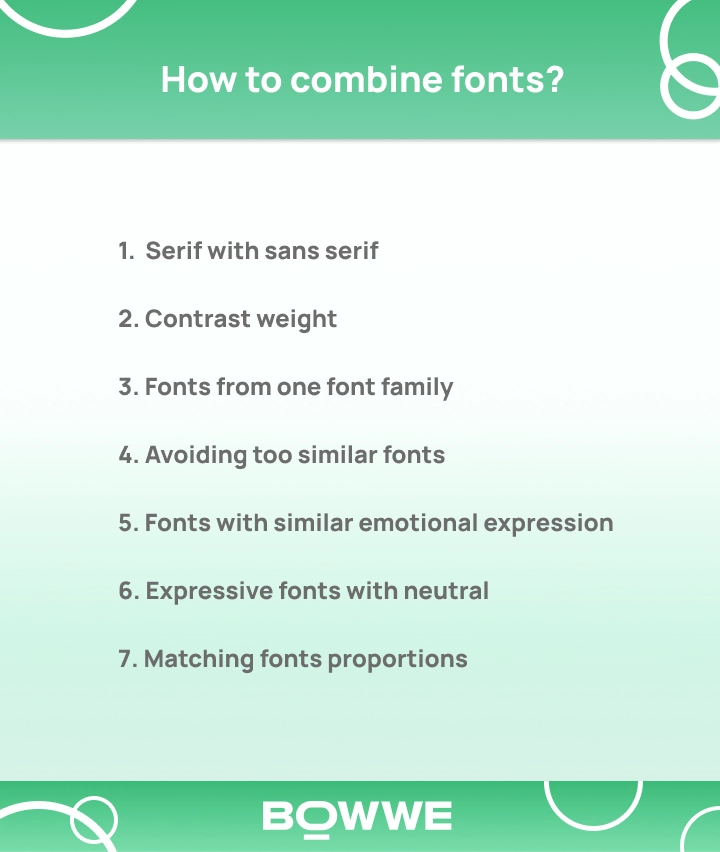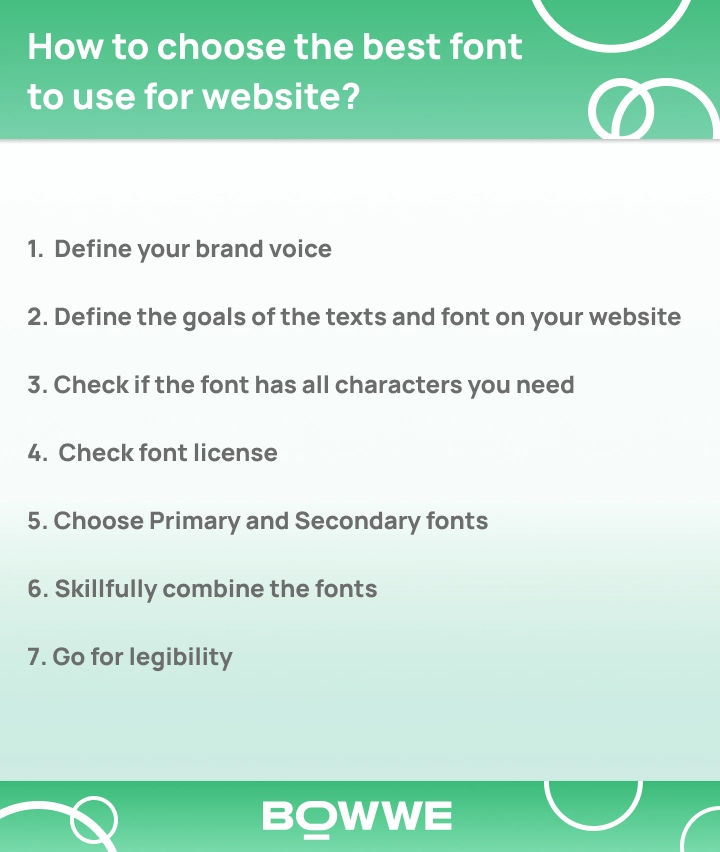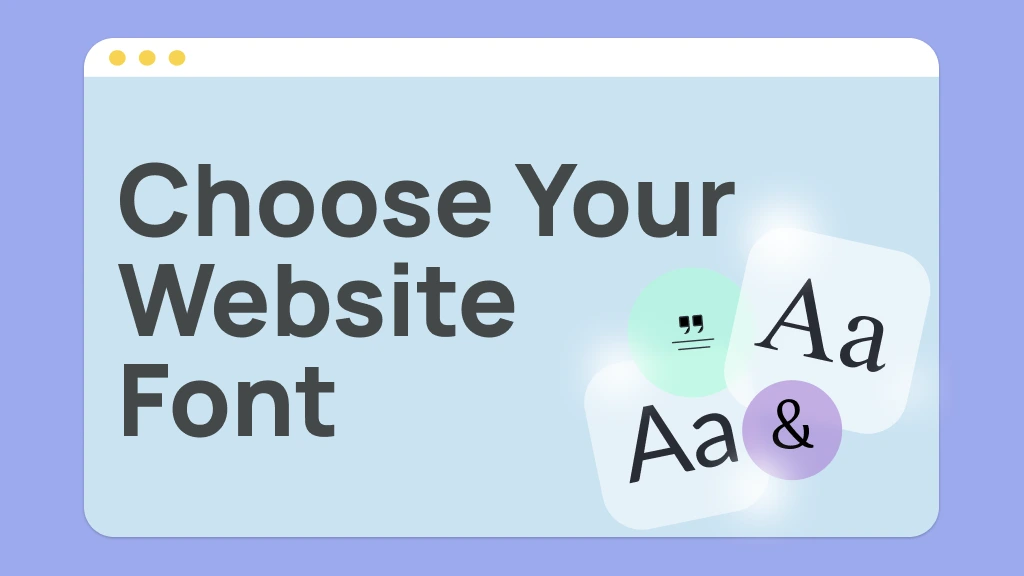
Aktualisieren oder erstellen Sie eine Website von Grund auf neu ? Jetzt ist es an der Zeit, die beste Schriftart auszuwählen. Dies ist eine entscheidende Wahl. Wieso den? Das Layout und Erscheinungsbild von Texten beeinflusst maßgeblich die Ästhetik, Funktionalität und Lesbarkeit der Website. Eine Website mit guten Schriftarten ist viel benutzerfreundlicher und führt zu einer höheren Conversion!
Die Auswahl der besten Schriftart für eine Website ist nicht einfach. Alles, was Sie tun müssen, ist dieser Anleitung zu folgen, um sicherzustellen, dass Sie die beste Webschriftart auswählen!
Wie wählt man die beste Schriftart für die Website aus?
Hier sind die 7 wichtigsten Schritte, die Sie unternehmen sollten!
1. Definieren Sie Ihre Markenstimme
2. Definieren Sie die Ziele der Texte und Schriftarten auf Ihrer Website
3. Überprüfen Sie, ob die Schriftart alle benötigten Zeichen enthält
4. Schriftartlizenz prüfen
5. Wählen Sie primäre und sekundäre Schriftarten
6. Kombinieren Sie die Schriftarten geschickt
7. Achten Sie auf Lesbarkeit
Werfen wir einen Blick darauf, wie man sie in der Praxis herstellt.
Schritt I: Definieren Sie Ihre Markenstimme
Wenn es um Schriftarten geht, ist Ihre Marke alles. Es ist das, was Kunden sehen und womit sie sich identifizieren, wenn sie an Ihr Unternehmen denken. Aus diesem Grund ist es so wichtig, dass Sie die richtige Schriftart für Ihr Unternehmen auswählen. Aber wie bestimmen Sie die Stimme Ihrer Marke? Und wie wählt man eine Schriftart aus, die das widerspiegelt?
Um die Art Ihrer Marke zu bestimmen, müssen Sie sich einige Fragen stellen:
1. Was sind die Werte Ihres Unternehmens?
2. Wer sind die Empfänger des Unternehmens?
3. Was ist Ihre Firmenmission?
4. Was sollen Ihre Kunden über Ihr Unternehmen denken?
Schreiben Sie die Antworten auf diese Fragen auf! Sie helfen Ihnen bei den nächsten Schritten bei der Schriftauswahl, die wir in diesem Artikel erläutern!
Schritt II: Definieren Sie die Ziele der Texte und Schriftarten auf Ihrer Website
In Bezug auf das Website-Design sind der von Ihnen gewählte Text und die Schriftart wichtig. Sie helfen dabei, den Ton anzugeben und Ihre Botschaft an die Besucher zu übermitteln. Was sind also die Ziele Ihres Textes und Ihrer Schriftart?
Der Text auf Ihrer Website sollte gut lesbar sein. Sie sollte groß genug sein, um schnell gesehen zu werden, und die Schriftart sollte leicht verständlich sein. Darüber hinaus ist es wichtig, auf Ihrer gesamten Website eine einheitliche Schriftart zu verwenden. Dies wird dazu beitragen, ein einheitliches Erscheinungsbild zu schaffen. Sie sollten auch wissen, wie wichtig die Rolle des Textes sein wird.
Bei manchen Websites spielt der Text keine große Rolle. Es wird zum Beispiel verwendet, um kurze Beschreibungen zu erstellen, daher kann seine Schriftart in diesem Fall dekorativer sein. Andererseits müssen diejenigen, die die meisten Informationen per Text (z. B. Blog) kommunizieren, sich in erster Linie darauf konzentrieren, dass sie bequem und leicht lesbar sind.
Die von Ihnen gewählte Schriftart sollte auch zum Inhalt Ihrer Website passen. Wenn Sie beispielsweise eine Unternehmenswebsite betreiben, möchten Sie möglicherweise eine Serifenschrift verwenden, um den Text professioneller erscheinen zu lassen. Umgekehrt, wenn Sie eine Website mit einem lässigeren Ton betreiben, möchten Sie vielleicht eine serifenlose Schriftart verwenden.
Kategorien von Schriftarten
Schriftarten werden hauptsächlich unterteilt in:
1. Serifenschriften
2. Sans-Serif-Schriftarten
3. Schreibschriften
4. Dekorative oder Anzeigeschriften
Serifenschriften
Diese Schriften haben quer oder diagonal verlaufende Linienabschlüsse (sogenannte Serifen), die die Schrift schmücken.
Die Verwendung von Serifen verleiht den Texten einen traditionellen, eleganteren Charakter. Diese Schriftarten werden seit langem in langen Papierpublikationen (hauptsächlich in Büchern) verwendet, da Serifen den Lesern helfen, der Textzeile zu folgen, wodurch sie leichter zu lesen sind.
Aufgrund ihres dekorativen Charakters machen Serifenschriften auch auf Websites eine gute Figur ... vor allem aber, wenn sie als zusätzliche Inhaltselemente eingesetzt werden, z
1. Überschriften,
2. Zitate,
3. Untertitel,
4. Logos,
5. Slogan
Sie können von Unternehmen genutzt werden, die ihre langjährige Erfahrung unterstreichen, auf Tradition verweisen und Sicherheit und Beständigkeit signalisieren wollen.
Beliebte Serifenschriften: Times New Roman, Georgia, Palatino, Bookman Old Style, Garamond, Courier, Lucida, Century, Arno Pro, MS Serif.
Sans-Serif-Schriftarten
Sans-Serif-Schriftarten sind frei von Serifen. Aus diesem Grund haben sie einen moderneren und minimalistischeren Charakter.
Ihr Einsatz im Internet ist alltäglich geworden, weil Bildschirme in der Vergangenheit Serifenschriften nicht korrekt darstellen konnten. Auch auf dem Bildschirm angezeigte serifenlose Schriften ermüden das Sehvermögen nicht.